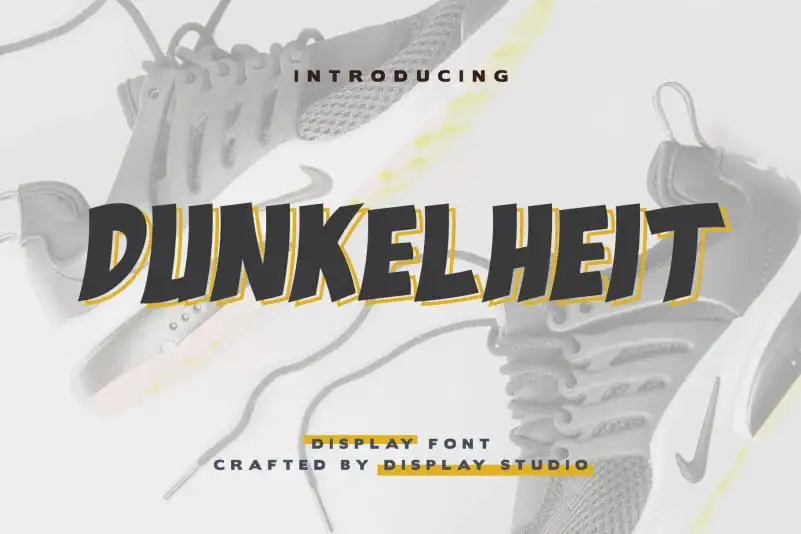
Dunkelheit Display Font – Download Grátis
Dunkelheit Display Font é uma fonte de display que traz a sensação encantadora de cortes de papel no estilo do logo final da animação. Inspirada nas tipografias usadas neste encerramento, esta fonte traz um toque amigável e brincalhão ao seu trabalho visual. Ideal para o logo de uma marca, cartas de convite ou mesmo qualquer projeto que exija uma identidade visual sólida e única. Com a versatilidade multilíngue e variedades de estilo, essa fonte não apenas adiciona um toque especial à sua arte, mas também eleva-a para níveis mais altos de beleza estética. Seja qual seja o projeto que você está trabalhando, Dunkelheit Display Font é uma escolha inegável para deixar seu trabalho ainda mais memorável e profissionalmente elaborado.